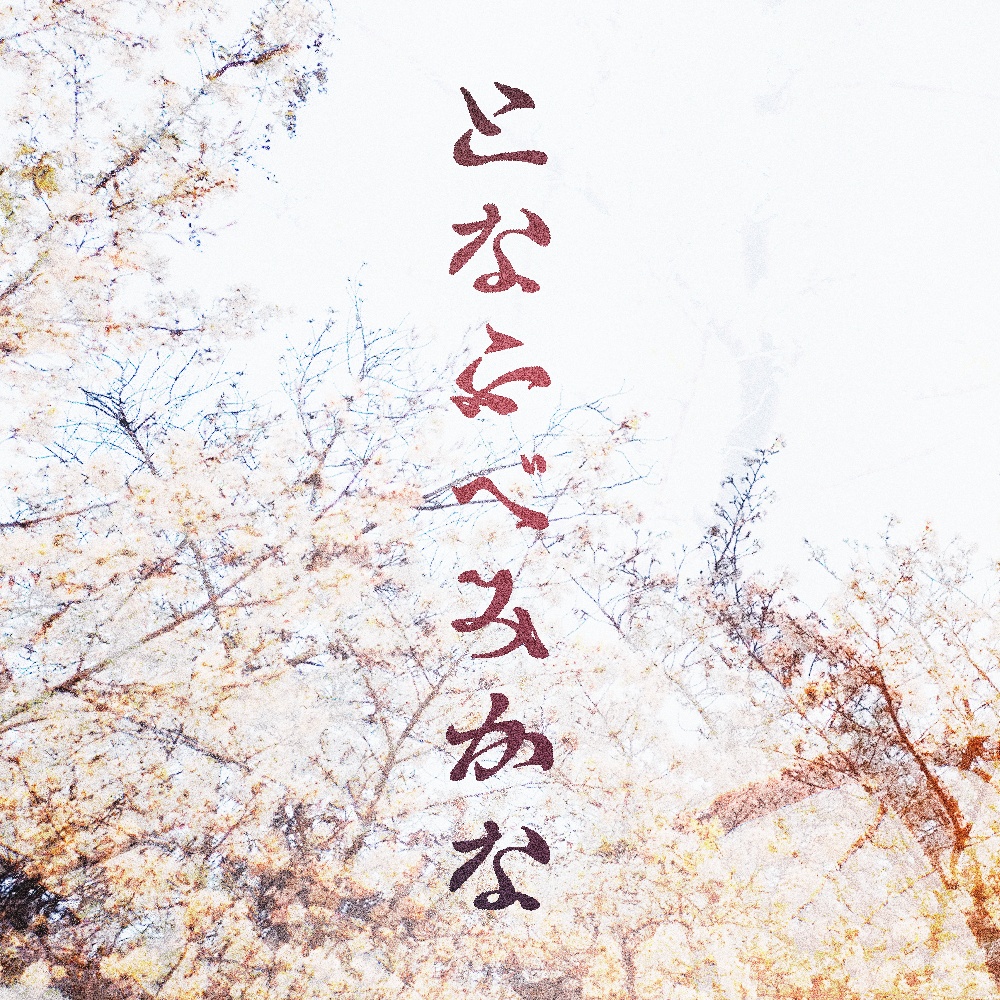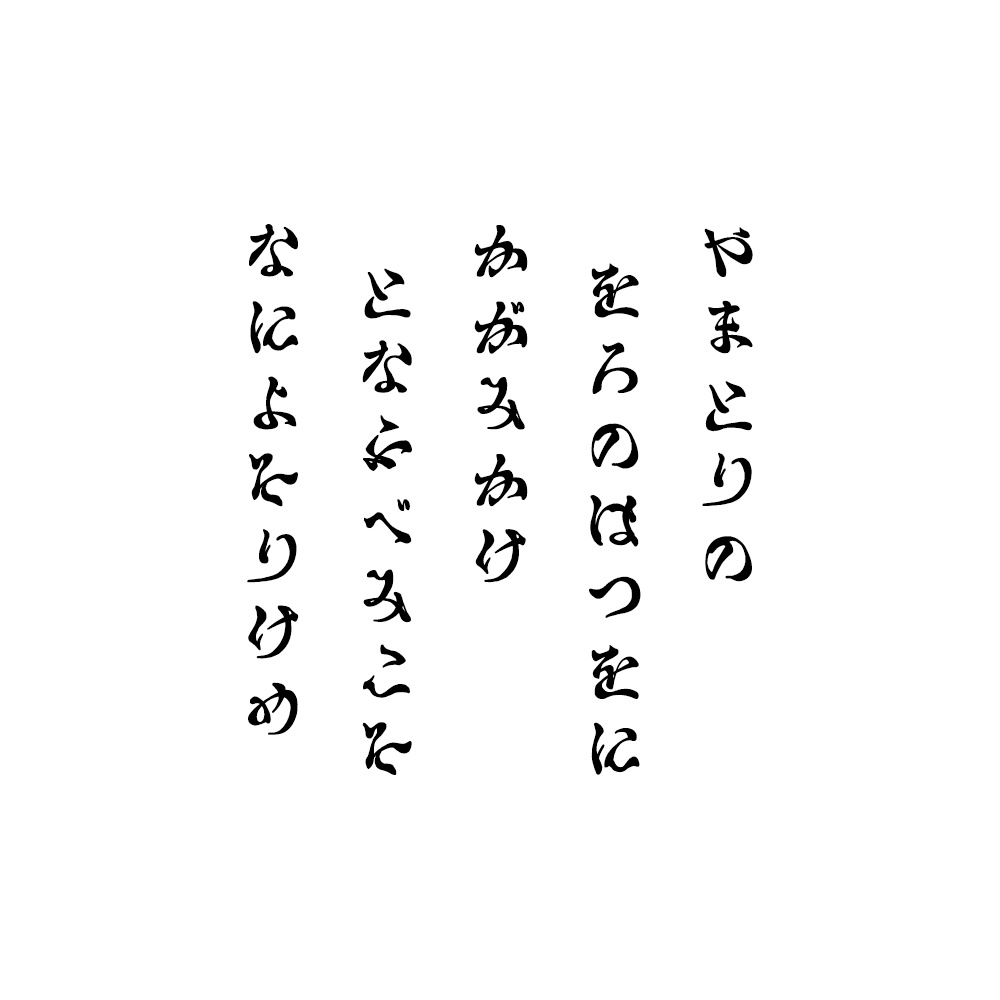
【かなフォント】唱ふべみかな
| 概要 唱ふべみかな は明朝かなフォントであり、以下の文字を収録します。 、。〜ぁあぃいぅうぇえぉおかがきぎくぐけげこごさざしじすずせぜそぞただちぢっつづてでとどなにぬねのはばぱひびぴふぶぷへべぺほぼぽまみむめもゃやゅゆょよらりるれろゎわゐゑをんゔ゛゜ゝゞ゠ァアィイゥウェエォオカガキギクグケゲコゴサザシジスズセゼソゾタダチヂッツヅテデトドナニヌネノハバパヒビピフブプヘベペホボポマミムメモャヤュユョヨラリルレロヮワヰヱヲンヴヵヶ・ーヽヾ~ | 利用条件 ・本フォントは、商用・非商用問わず使用可能です。 ・本フォントの使用範囲には、印刷物・画像化したデータ・映像作品・ウェブサイトでの利用を含みます。 ・フォントファイルを直接配布することはできません。 ・電子文書(PDF等)、アプリケーション、ウェブフォント等への埋め込みは、フォントデータを第三者が抽出できない状態でのみ許可します。 | 禁止事項 ・フォントファイルそのもの、または抽出可能な状態のデータの再配布・販売。 ・フォントを改変して新たなフォントとして配布・販売する行為。 ・公序良俗に反するコンテンツ、または違法行為を助長する目的での使用。 | 免責事項 ・本フォントの利用によって生じたいかなる損害についても、作者は一切の責任を負いません。 ・仕様は予告なく変更される場合があります。(たとえばグリフ形状について品質の改善のためアップデートによって変更されることがあります。)